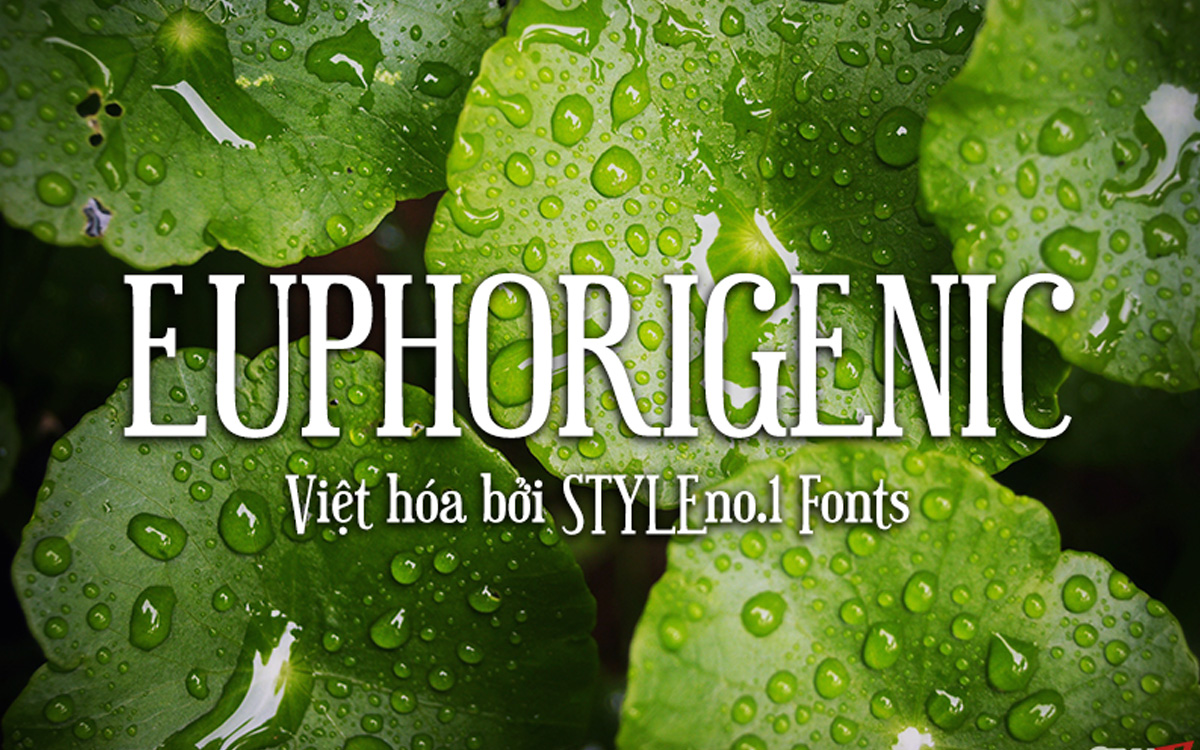
Font chữ sang trọng, hiện đại, thanh lịch cho lễ cưới, tạp chí, thời trang SVN-Euphorigenic
SVN-Euphorigenic là font chữ mang phong cách sang trọng, hiện đại và thanh lịch, được thiết kế để tạo nên dấu ấn thị giác tinh tế cho lễ cưới, tạp chí, thời trang và các dự án xây dựng thương hiệu cao cấp. Với đường nét mềm mại, tỷ lệ chữ cân đối và tinh thần nghệ thuật đầy cuốn hút, font SVN-Euphorigenic giúp mỗi tiêu đề, lời mời hay thông điệp trở nên nổi bật mà vẫn giữ được vẻ trang nhã, chuyên nghiệp.
Không chỉ phù hợp với những thiết kế lãng mạn, SVN-Euphorigenic còn có khả năng ứng dụng linh hoạt trong nhiều lĩnh vực sáng tạo. Đây là lựa chọn đáng cân nhắc dành cho nhà thiết kế đồ họa, studio cưới, thương hiệu thời trang, biên tập viên tạp chí, người làm nội dung và bất kỳ ai đang tìm kiếm một font chữ đẹp để nâng cao giá trị thẩm mỹ cho sản phẩm.
Font chữ sang trọng, hiện đại và thanh lịch SVN-Euphorigenic dành cho lễ cưới, tạp chí, thời trang cao cấp
Trong thiết kế, font chữ không chỉ có nhiệm vụ truyền tải nội dung mà còn quyết định cảm xúc, phong cách và mức độ chuyên nghiệp của toàn bộ ấn phẩm. SVN-Euphorigenic sở hữu diện mạo thanh lịch, giàu tính thời trang, phù hợp với những bố cục cần sự mềm mại nhưng không quá cầu kỳ. Các đường nét uyển chuyển kết hợp cùng cấu trúc chữ hiện đại giúp font tạo được điểm nhấn rõ ràng ngay từ cái nhìn đầu tiên.
Font chữ sang trọng SVN-Euphorigenic đặc biệt phù hợp với các tiêu đề lớn, tên thương hiệu, tên cô dâu chú rể, bìa tạp chí hoặc thông điệp quảng cáo ngắn. Khi được kết hợp với khoảng trắng hợp lý, màu sắc tinh tế và một font chữ phụ dễ đọc, SVN-Euphorigenic có thể góp phần tạo nên hệ thống nhận diện đồng nhất, giàu cảm xúc và có chiều sâu.
Thiết kế thiệp cưới và ấn phẩm lễ cưới đầy lãng mạn
SVN-Euphorigenic là lựa chọn nổi bật cho những thiết kế liên quan đến lễ cưới nhờ vẻ đẹp mềm mại, trang trọng và giàu cảm xúc. Font có thể được sử dụng để trình bày tên cô dâu chú rể, ngày tổ chức, lời chúc, tiêu đề chương trình hoặc những câu trích dẫn ý nghĩa. Phong cách thanh lịch của kiểu chữ giúp thiệp cưới trở nên tinh tế, tạo cảm giác chỉn chu ngay cả khi bố cục được thiết kế theo hướng tối giản.
Ngoài thiệp mời truyền thống, font còn có thể ứng dụng trên nhiều hạng mục khác trong bộ nhận diện lễ cưới, bao gồm:
• Thiệp báo hỷ, thiệp cảm ơn và thiệp mời điện tử.
• Bảng chào đón khách mời, sơ đồ bàn tiệc và bảng tên.
• Menu tiệc cưới, số bàn, phong bì và tem dán quà tặng.
• Album ảnh cưới, video kỷ niệm và bài đăng trên mạng xã hội.
• Backdrop sân khấu, photobooth và các vật phẩm trang trí.
Để bảo đảm nội dung dễ đọc, người thiết kế có thể dùng SVN-Euphorigenic cho các dòng chữ cần nhấn mạnh, sau đó kết hợp với một font sans serif hoặc serif đơn giản cho phần thông tin chi tiết. Cách phối hợp này vừa giữ được nét lãng mạn, vừa giúp toàn bộ ấn phẩm cân bằng và rõ ràng.
Tạo tiêu đề tạp chí nổi bật và giàu tính biên tập
Đối với thiết kế tạp chí, tiêu đề cần đủ ấn tượng để thu hút người xem nhưng vẫn phải phù hợp với chủ đề và phong cách nội dung. SVN-Euphorigenic mang đến vẻ ngoài hiện đại, nghệ thuật, thích hợp cho bìa tạp chí, tiêu đề chuyên mục, trang mở đầu hoặc các câu trích dẫn nổi bật. Những đường nét có tính biểu cảm giúp nội dung trở nên sinh động, đồng thời tạo cảm giác cao cấp cho bố cục.
Font có thể được sử dụng trong các ấn phẩm về thời trang, phong cách sống, làm đẹp, nghệ thuật, nhiếp ảnh, du lịch hoặc nội thất. Khi đặt trên nền ảnh có độ tương phản tốt, SVN-Euphorigenic giúp tiêu đề trở thành tâm điểm mà không làm mất đi giá trị của hình ảnh. Người dùng cũng có thể điều chỉnh kích thước, khoảng cách chữ và vị trí trình bày để tạo nên nhiều sắc thái khác nhau, từ tối giản, trẻ trung đến cổ điển và quyến rũ.
Nâng tầm thiết kế thời trang và nhận diện thương hiệu
Trong lĩnh vực thời trang, kiểu chữ là một phần quan trọng giúp thương hiệu thể hiện cá tính. SVN-Euphorigenic phù hợp với các nhãn hàng muốn xây dựng hình ảnh thanh lịch, nữ tính, hiện đại hoặc mang hơi hướng boutique cao cấp. Font có thể xuất hiện trong logo dạng chữ, bộ sưu tập theo mùa, lookbook, catalogue, banner quảng cáo, bao bì, nhãn mác và nội dung truyền thông.
Với khả năng tạo điểm nhấn tốt, SVN-Euphorigenic hỗ trợ truyền tải tinh thần của những sản phẩm như váy cưới, trang phục thiết kế, mỹ phẩm, nước hoa, phụ kiện, trang sức hoặc dịch vụ làm đẹp. Để hình ảnh thương hiệu nhất quán hơn, người thiết kế nên xây dựng quy tắc sử dụng font cụ thể:
đọc.
• Kết hợp với font serif để tăng vẻ cổ điển, sang trọng và mang tính biên tập.
• Sử dụng màu đen, trắng, kem hoặc vàng ánh kim cho thiết kế cao cấp.
Một ưu điểm đáng chú ý của SVN-Euphorigenic là khả năng kết hợp với nhiều phong cách hình ảnh. Font có thể xuất hiện trong thiết kế tối giản với nền sáng và nhiều khoảng trắng, hoặc trong bố cục giàu cảm xúc với hoa lá, chất liệu giấy, đường viền cổ điển và hiệu ứng ánh kim. Đối với phong cách hiện đại, hãy kết hợp font cùng hình ảnh thời trang có bố cục mạnh, màu tương phản và các khối hình học rõ nét.
Người dùng có thể tham khảo một số hướng phối hợp phổ biến như:
• Kết hợp với font sans serif để tạo cảm giác hiện đại, sạch sẽ và dễ